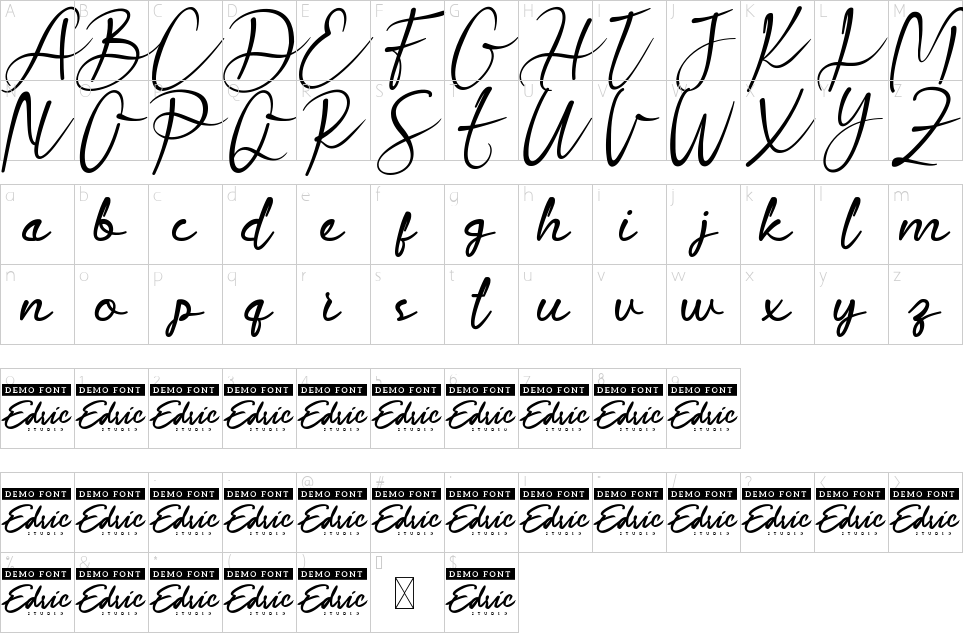
A Dalisha é uma elegante fonte gráfica que oferece um estilo versátil e sofisticado para qualquer projeto editorial ou design. Desenvolvida pelo EdricStudio, essa fonte adquire uma personalidade única através de suas linhas leves e seu desenho delicado. Suas métricas cuidadosamente programadas garantem a legibilidade precisa em qualquer tamanho de texto, tornando-a ideal para uso tanto em aplicativos como em projetos impressos. Ideal tanto para uso pessoal quanto em trabalhos profissionais, Dalisha oferece uma versão gratuita disponível no Windows e Mac. Com seu design cuidadosamente refinado e sua facilidade de uso, a fonte Dalisha é o escolha perfeita para aqueles procurando por um toque sofisticado sem comprometer o conforto da leitura. Engajada e pronta para ser usada, a Dalisha estará sempre ao seu lado no processo de criação visual.